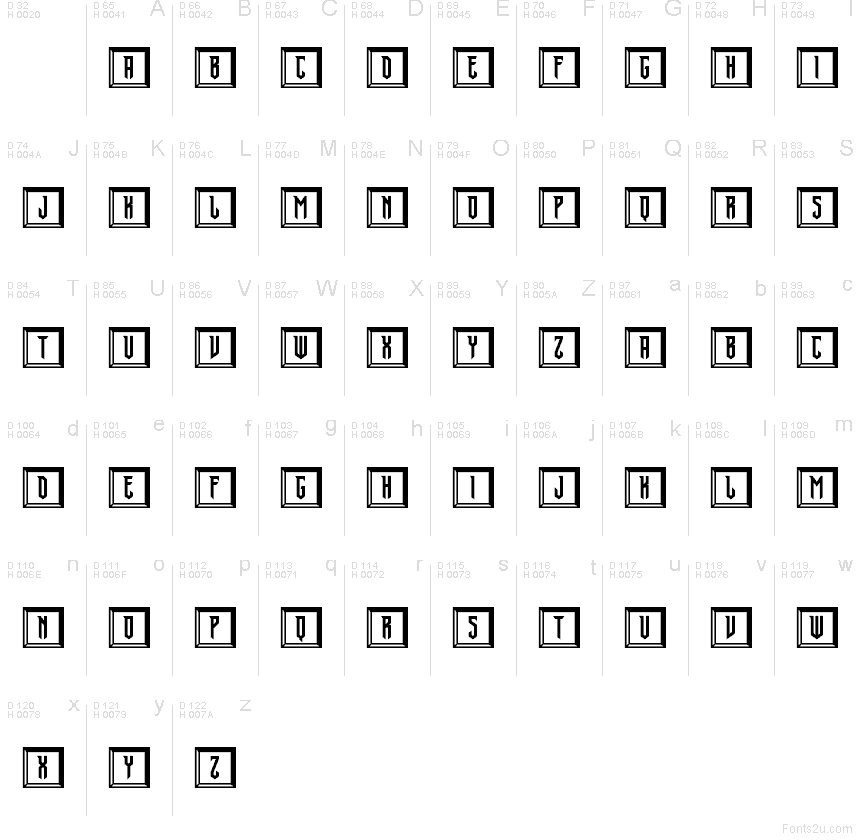
Lazarus Of Bethany Flat, une police d'initiales gothiques gratuite créée par Vladimir Nikolic, plonge dans une atmosphère médiévale blackletter avec ses lettres hautes et étroites aux formes anguleuses et rigides. L'emphase verticale répétée et les encoches intérieures tranchantes donnent aux caractères un aspect sculpté et héraldique, tandis que le cadrage plat maintient un style net, loin d'être trop ornemental.
Cette police gratuite prend tout son sens là où vous souhaitez apporter une touche solennelle et ancienne : couvertures de livres, logos de groupes, titres d'affiches, ouvertures de chapitres et monogrammes s'accordent parfaitement à son rythme sévère. Elle fonctionne mieux dans des compositions courtes, où ces formes gothiques pointues suffisent à installer l'atmosphère sans nécessiter beaucoup de texte.